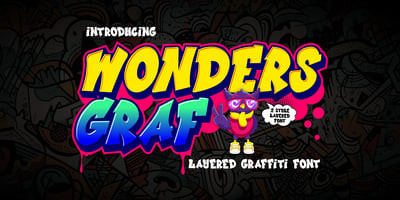
Wonders Graf 3d Graffiti Yazı Tipi, dinamik, kentsel ve belirgin bir grafiti estetiği arayan tasarımlar için mükemmel bir seçimdir; sokak sanatının ham enerjisini ve cesur ifadesini yansıtmak için idealdir. Onu, hip-hop albüm kapaklarında, kaykay markalarının logolarında veya sokak giyim tasarımlarına asi ve sanatsal bir hava katarken hayal edin. Ayrıca, gençlik etkinlikleri için dikkat çekici poster tasarımları, video oyun tanıtımları ve yaratıcı, enerjik bir his uyandırmak istediğiniz her proje için mükemmeldir. Kalın, akıcı vuruşları ve genellikle üç boyutlu veya katmanlı görünümüyle Wonders Graf 3d Graffiti Yazı Tipi, görsel etki ve unutulmaz, cesur bir izlenim bırakmayı hedefleyen projeler için idealdir.
Wonders Graf 3d Graffiti Yazı Tipi'ni gerçekten heyecan verici kılan şey, tasarımlara anında bir sokak sanatı ruhu ve kentsel bir dinamizm katabilmesidir. Gerçek bir grafiti sanatçısının elinden çıkmış gibi hissettirir, tasarımlarınıza anında bir otantiklik ve dışavurumculuk katar. Görünür dokular, değişen vuruş genişlikleri ve harflerin doğal akışı, otantik grafiti yazımını taklit ederek hem çarpıcı hem de son derece etkileyici bir görsel stil yaratır. Bu yazı tipi, sanatsal, cesur ve özgün bir marka kimliği oluşturmak için mükemmeldir, görsel iletişiminizin sadece görülmesini değil, aynı zamanda gerçekten hissedilmesini sağlar. Wonders Graf 3d Graffiti Yazı Tipi Ücretsiz İndirme, projelerinize bu ayırt edici karakteri katmak için harika bir fırsat sunar.
Wonders Graf 3d Graffiti Yazı Tipi ailesi, genellikle kendine özgü ve cesur stilini korurken çok yönlülük sunmak üzere tasarlanmıştır. Belirli aile üyeleri değişebilir, ancak genellikle şunları bulmayı bekleyebilirsiniz:
Wonders Graf 3d Graffiti Regular: Belirgin üç boyutlu veya katmanlı grafiti stili.
Wonders Graf 3d Graffiti Outline: Yalnızca dış hatları sunan tamamlayıcı bir sürüm, katmanlama ve benzersiz renk kombinasyonlarına olanak tanır.
Wonders Graf 3d Graffiti Shadow: Daha belirgin bir gölge veya derinlik efekti için.
Wonders Graf 3d Graffiti Slanted (veya Italic): Daha dinamik, öne eğik bir görünüm için.
Wonders Graf 3d Graffiti Alternates: Doğal el yazısı görünümünü geliştirmek ve yaratıcı varyasyonlar sağlamak için stilistik alternatifler veya ligatürler içerebilir.
Bu varyasyonlar, farklı tasarım uygulamaları için esneklik sağlayarak, ilgi çekici görsel hiyerarşiler oluşturmanıza ve tüm projelerinizde tutarlı, güçlü bir estetik sürdürmenize olanak tanır.